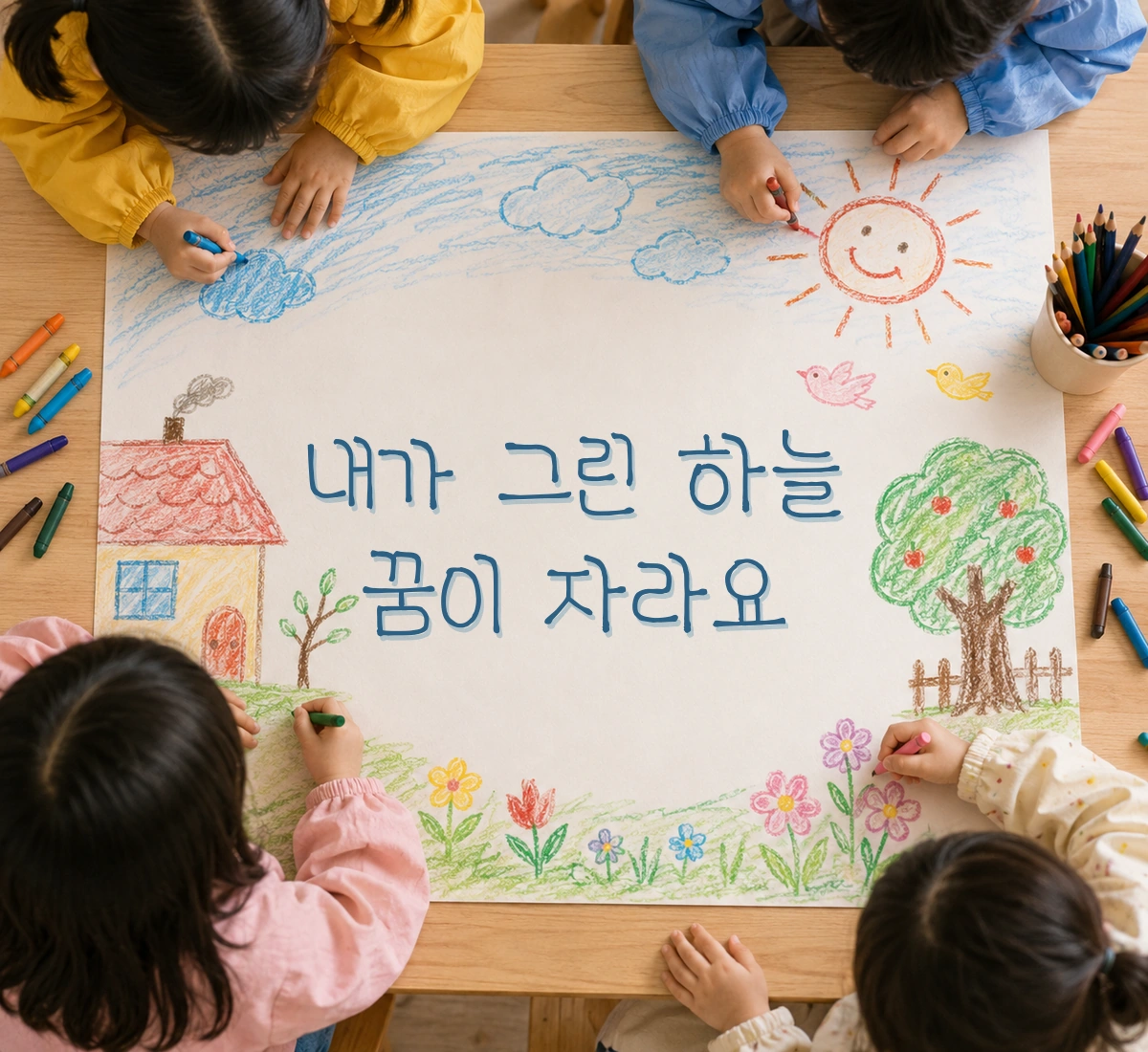
ACC 어린이 하늘맑은체 — 국립아시아문화전에서 배포하는 무료 폰트입니다. 둥글둥글한 자음과 힘차게 뻗은 획이 어우러진 귀엽고 정겨운 손글씨체
국립아시아문화전당이 2021년 12월에 무료로 푼 서체 세 벌 가운데 하나입니다. 세 벌 모두 **전국 초등학생을 대상으로 연 손글씨 공모전에서 입상한 어린이들의 글씨**를 폰트로 옮긴 것이고, 글꼴 이름도 어린이들의 의견을 반영해 정했습니다.
조형 설명에서 한 가지 짚을 것이 있습니다. 전당의 현행 소개 페이지는 둥글둥글한 모양의 자음이 특징이며 어린이 손글씨 느낌을 그대로 살린 귀여운 서체라고 적었는데, 2021년 배포자료에는 같은 서체를 두고 직선으로 힘차게 뻗은 획과 약간의 기울기가 눈에 띈다고 적혀 있습니다. 같은 기관의 두 문서가 어긋나고, 뒤쪽 문장은 지금 다른 서체에 붙어 있습니다.
그래서 형태는 파일을 보고 적습니다. 받침이 붙을 때 글자 높이가 달라지는 탈네모틀이고 낱자는 정사각형에 가까우며, 획이 가늘어 자면을 채우는 비율이 낮습니다. 어린이가 또박또박 눌러 쓴 인상에 가깝습니다.